Dalam dunia olahraga, jersey bukan hal yang sepele. Selain sebagai identitas, jersey sering kali dijadikan sebagai bagian penting dalam membangun citra dan semangat tim. Namun, bukan hanya soal warna dan motif baju, penggunaan font jersey juga nyatanya memiliki peran yang signifikan dalam membuat desain jersey semakin menonjol dan unik.
Font yang biasanya digunakan untuk desain nomor dan nama pemain ini menjadi salah satu faktor penentu dalam keseluruhan estetika jersey. Dengan memilih font jersey yang tepat, desain jersey dapat menjadi lebih menarik, khas, dan memberikan kesan yang kuat di lapangan. Apabila Anda sedang mencari font jersey terbaik, di bawah ini kami telah mengumpulkan 45 rekomendasi font jersey keren yang bisa Anda unduh dan gunakan secara gratis! Yuk, simak daftarnya berikut ini!
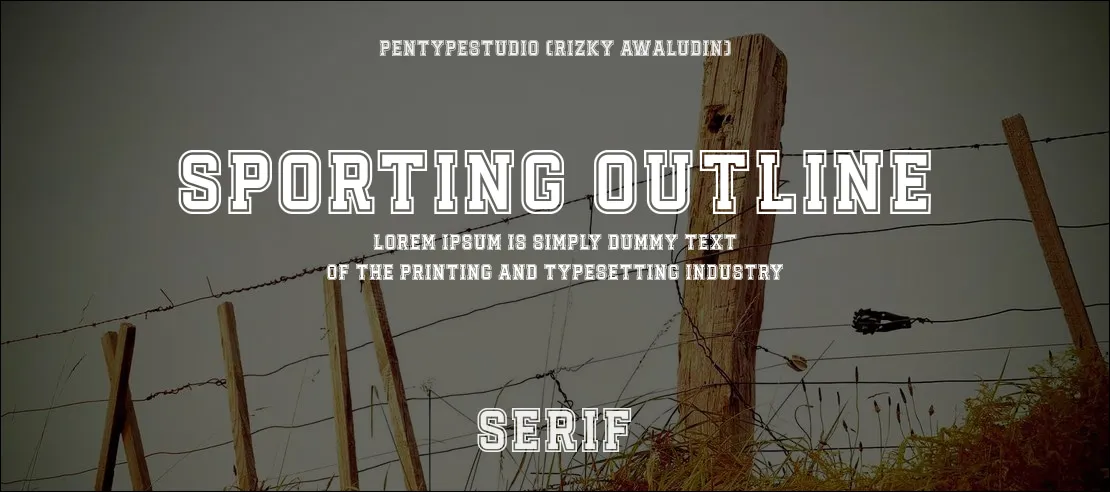
Font pertama adalah Sporting Outline. Font ini memiliki garis tepi yang jelas dan tegas, memberikan kesan yang energik. Cocok digunakan untuk desain jersey yang memerlukan penampilan sporty dan modern.
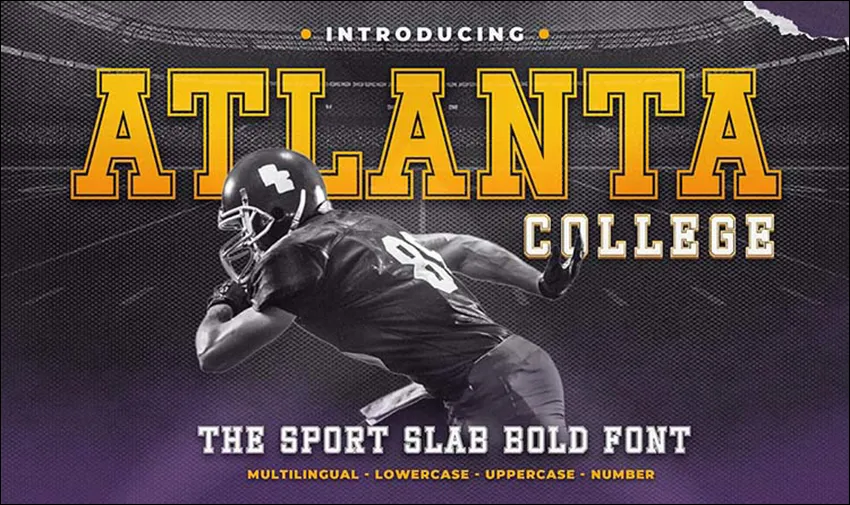
Font kedua adalah Atlanta College. Font bold ini menggabungkan elemen-elemen tradisional dengan sentuhan modern, menciptakan nuansa klasik yang cocok untuk desain jersey tim olahraga perguruan tinggi atau sekolah.
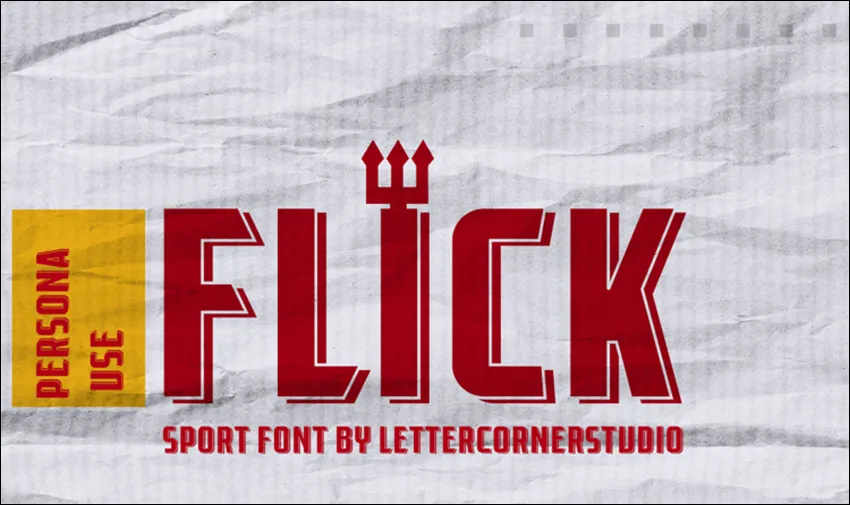
Selanjutnya adalah font Flick. Dengan desain modern, ukuran sedang, dan ujung-ujung yang tajam, font ini memberikan kesan yang segar dan bersemangat. Cocok digunakan untuk jersey tim yang ingin terlihat aktif dan penuh semangat.
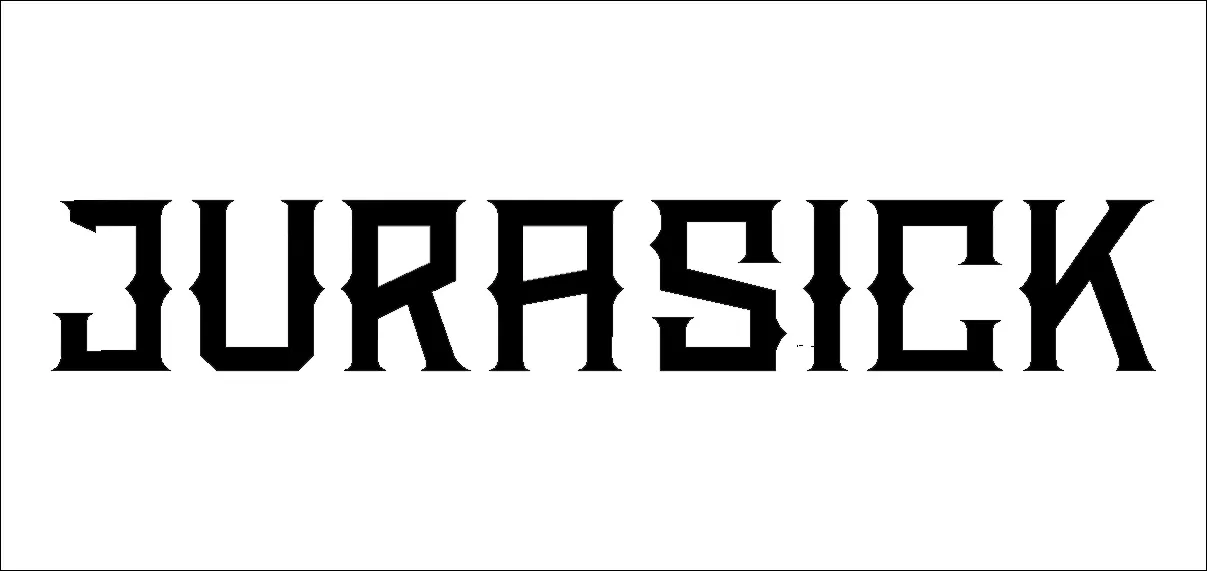
Font ini memiliki desain yang unik dan menarik, dengan goresan-goresan artistik yang menonjolkan keberanian dan kekuatan. Cocok digunakan untuk jersey tim yang ingin tampil berbeda dan mencolok.
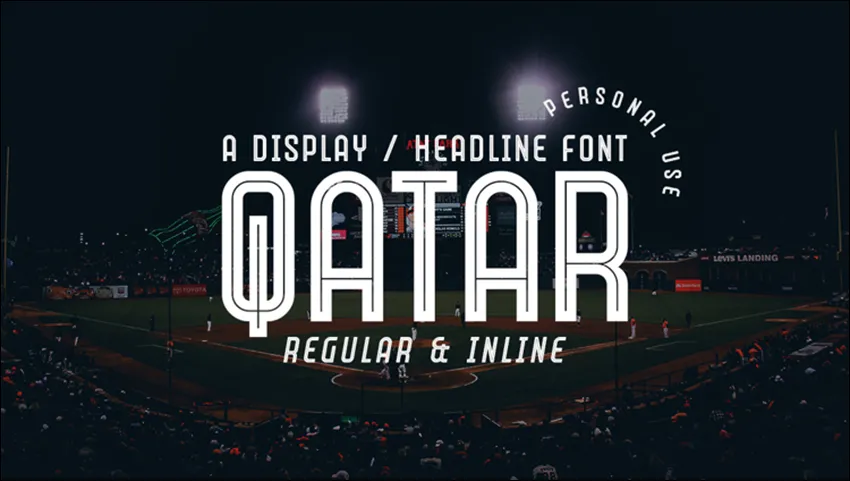
Dengan bentuk huruf yang tegak dan elegan, font ini cocok untuk jersey tim yang ingin tampil profesional dan berkelas.
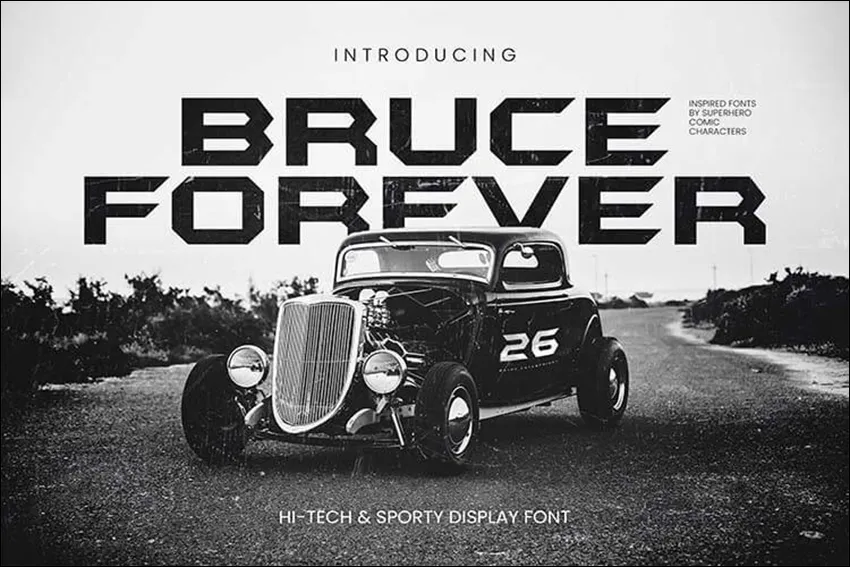
Bruce Forever memberikan kesan yang kuat dan tangguh dengan garis-garis yang kokoh dan tajam, terinspirasi dari karakter komik superhero Batman. Cocok digunakan untuk jersey tim yang ingin menampilkan keberanian dan ketangguhan.
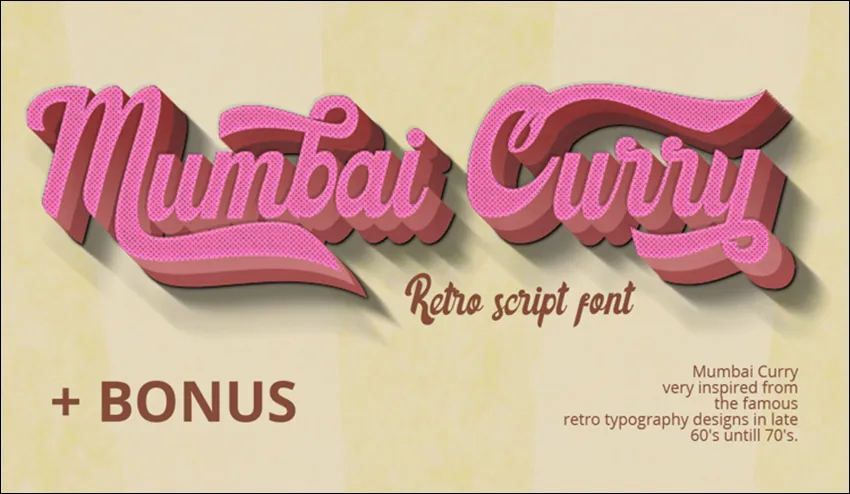
Mumbai Curry terinspirasi oleh font pada awal tahun 70an, memberikan nuansa yang eksotis dan unik, cocok untuk tim olahraga yang ingin tampil aesthetic.
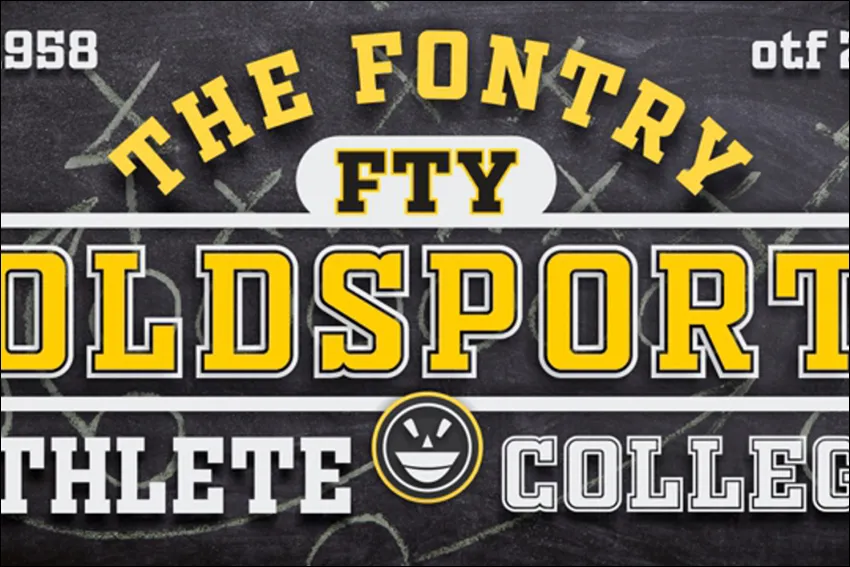
Dengan desain yang klasik dan legendaris, font ini cocok untuk jersey tim yang ingin tampil dengan nuansa retro yang elegan.
Font serif ini menciptakan nuansa retro dan nostalgik, cocok untuk tim olahraga yang ingin menampilkan sentuhan klasik dalam desain jersey mereka.
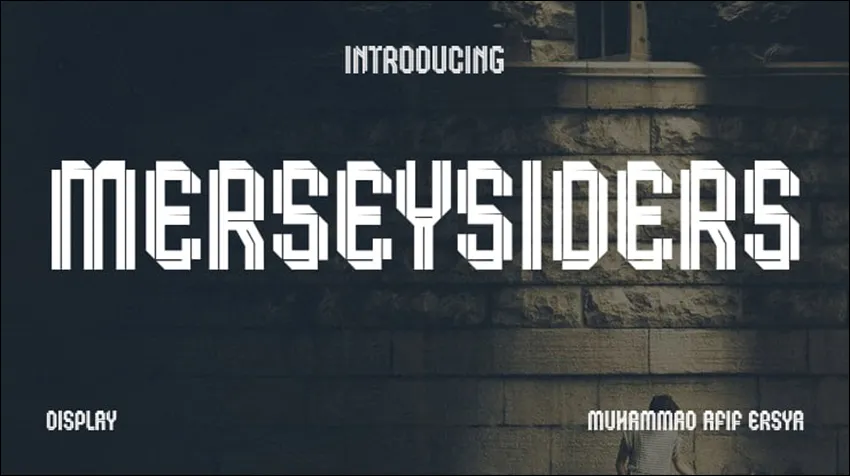
Terinspirasi dari font jersey milik Liverpool FC pada tahun 2022-2023, Merseysiders menggabungkan elemen modern dengan nuansa tradisional, menciptakan kesan yang unik dan berkelas untuk jersey tim olahraga bola.
Dengan desain vintage yang keren dan mewah, font ini cocok untuk jersey tim yang ingin tampil menyala meski dalam kondisi gelap malam.
Font ini sering kali dipakai dalam desain jersey eSport, memberikan tampilan bold dan modern, cocok untuk tim eSport atau gaming yang ingin menampilkan semangat bertanding dalam desain jersey mereka.
Dengan desain kuno yang mewah, font ini cocok untuk tim olahraga yang ingin menampilkan kegigihan dan semangat baru dari para pemain muda.
Font Campus memiliki desain bold dengan sedikit terkikis di beberapa bagian karakternya, cocok untuk jersey tim olahraga kampus atau sekolah.
Dengan gaya tulisan yang elegan dan artistik, font ini cocok untuk jersey tim olahraga baseball yang ingin menampilkan kesan berkelas dan profesional.
Font ini memiliki desain yang simple, bold, namun tetap modern, cocok untuk jersey tim olahraga yang ingin tampil dengan gaya yang sederhana namun tetap menarik.
Dengan desain sporty yang bold dan keren, font ini cocok untuk jersey tim olahraga balapan.yang ingin menampilkan semangat menang dalam pertandingan.
Font ini memiliki 4 model dengan keunikan masing-masing. Cocok untuk jersey tim olahraga sepak bola atau eSport.
Dengan desain kampus klasik dan efek handmade yang keren, font ini cocok untuk jersey tim olahraga rugby, sepak bola, dan lain-lain.
Superstar M54 menciptakan kesan yang megah dan menonjol dengan desainnya yang bold, cocok untuk jersey tim olahraga sepak bola universitas.